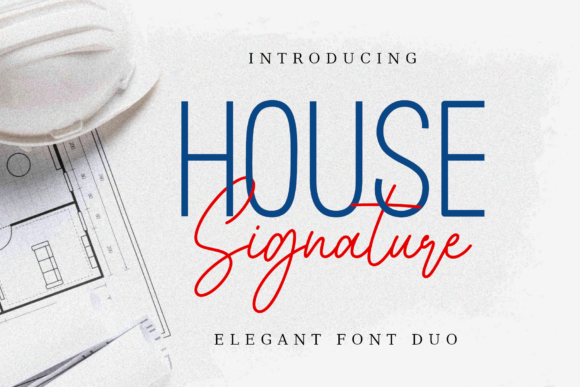
[Creativefabrica] House Signature Font (2021)
House Signature - это элегантный и нежный шрифт в дуэте (sans serif и script).
Он обладает красивыми и хорошо сбалансированными символами и, как следствие, подходит для широкого круга дизайнов.